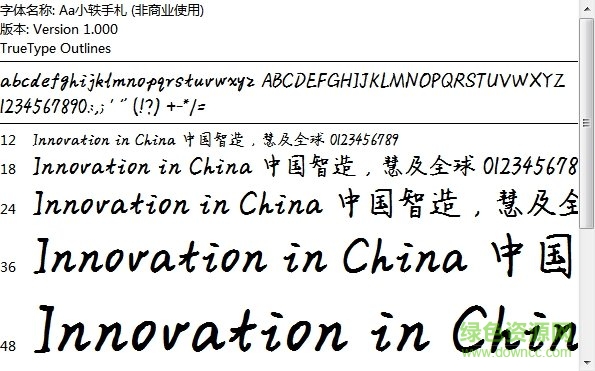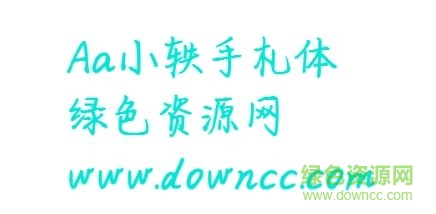
Aa小軼手札體,也叫作Aa小蟻手札體,是一款風(fēng)格靚麗、豪邁大氣的手寫(xiě)體,支持中英文、繁簡(jiǎn)體和日文輸入,字庫(kù)比較完整,來(lái)綠色資源網(wǎng)免費(fèi)擁有吧!
真正的女漢子獨(dú)立且自立,要有一顆擔(dān)當(dāng)?shù)男?,要不斷的沖破堡壘,還要?jiǎng)側(cè)岵?jì),字體棱角的分明代表了我們不拘一格的個(gè)性,筆劃轉(zhuǎn)折的柔韌代表了我們女生貴在的特質(zhì),乖乖女已經(jīng)成長(zhǎng),你們可以放心了!
小軼手札有字咖設(shè)計(jì),滿(mǎn)足了常規(guī)文字的使用,更支持日文顯示,字跡清晰而平穩(wěn),沒(méi)有浮夸和不正經(jīng)之氣,給人十分舒適的視覺(jué)體驗(yàn),用于排版印刷、海報(bào)設(shè)計(jì)、廣告創(chuàng)意也挺合適。